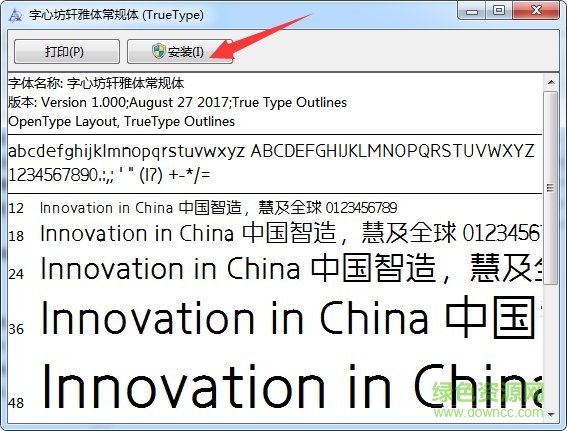
字心坊軒雅體是一款風(fēng)格時尚、簡約標志的無襯線字體,字庫完整使用廣泛,有著極佳的視覺效果,給你的設(shè)計增添更多光彩,快來綠色資源網(wǎng)試試吧!
該字體為字心坊軒雅體字體系列作品的細款字型字體。字體采用非襯線設(shè)計,全部筆畫采用直線設(shè)計。字體個性鮮明,字形特點時尚新穎,同時融入古風(fēng)結(jié)構(gòu),靈活多變的線條造就此款字體的與眾不同。
字心坊軒雅體是字心坊全新上線的常規(guī)字體,可以使用在較多的場景當(dāng)中,給大家的設(shè)計帶來更多的藝術(shù)體驗。